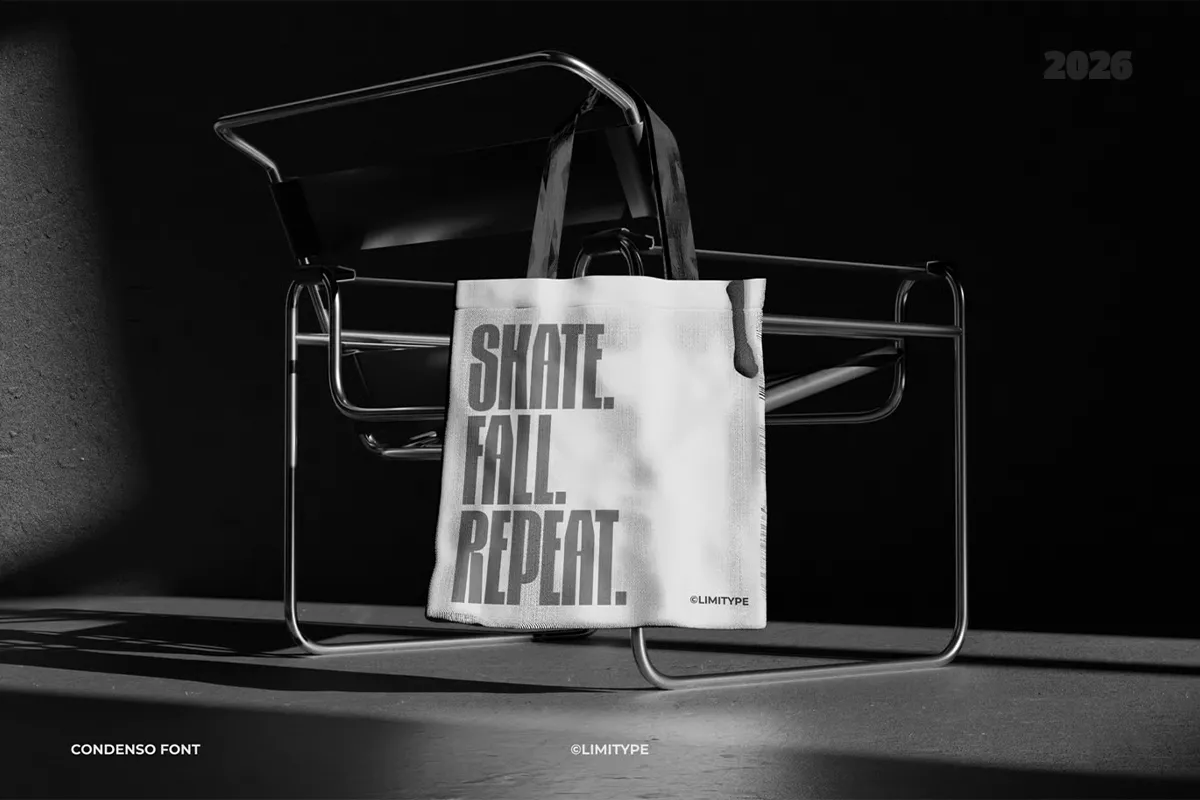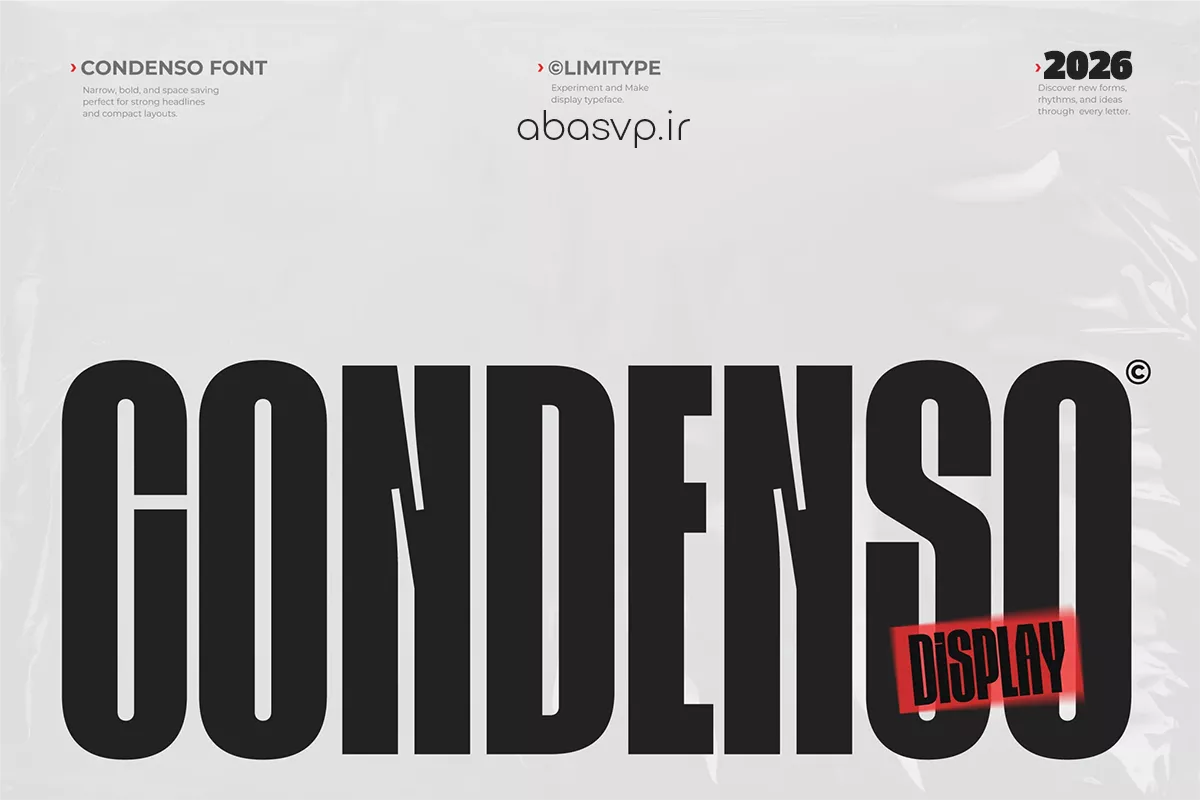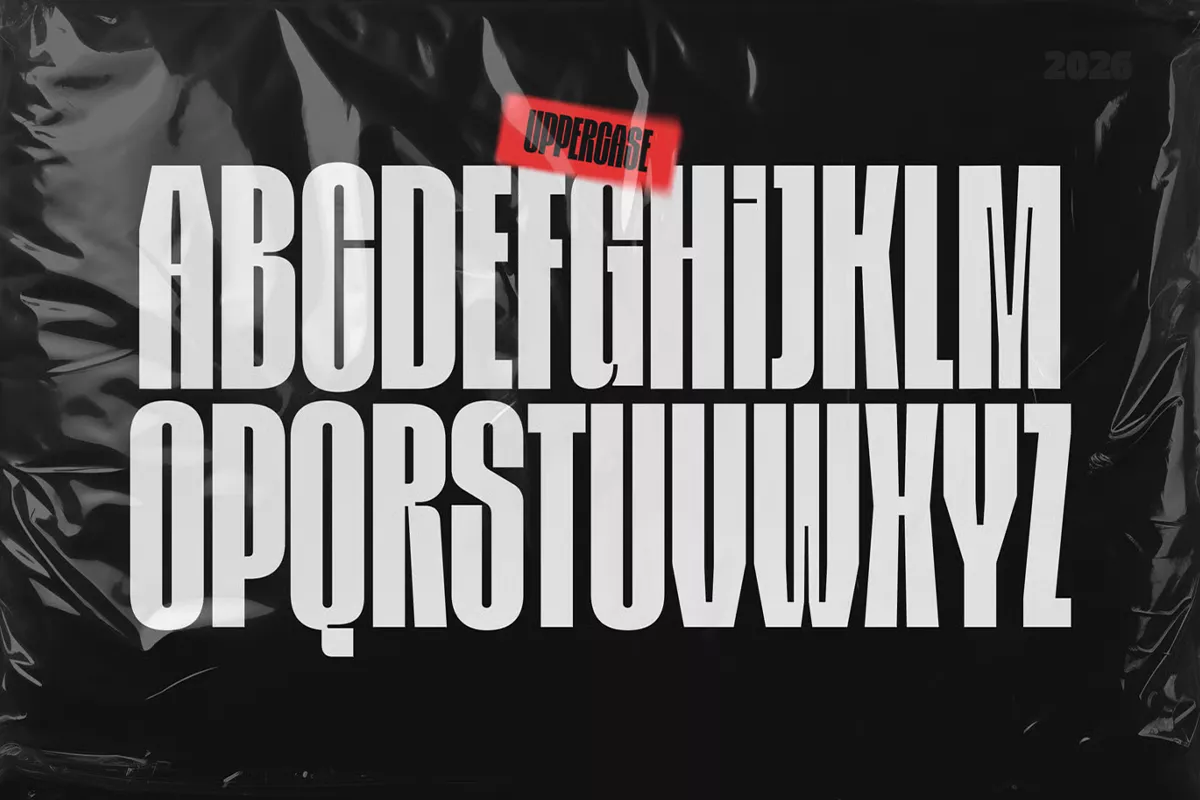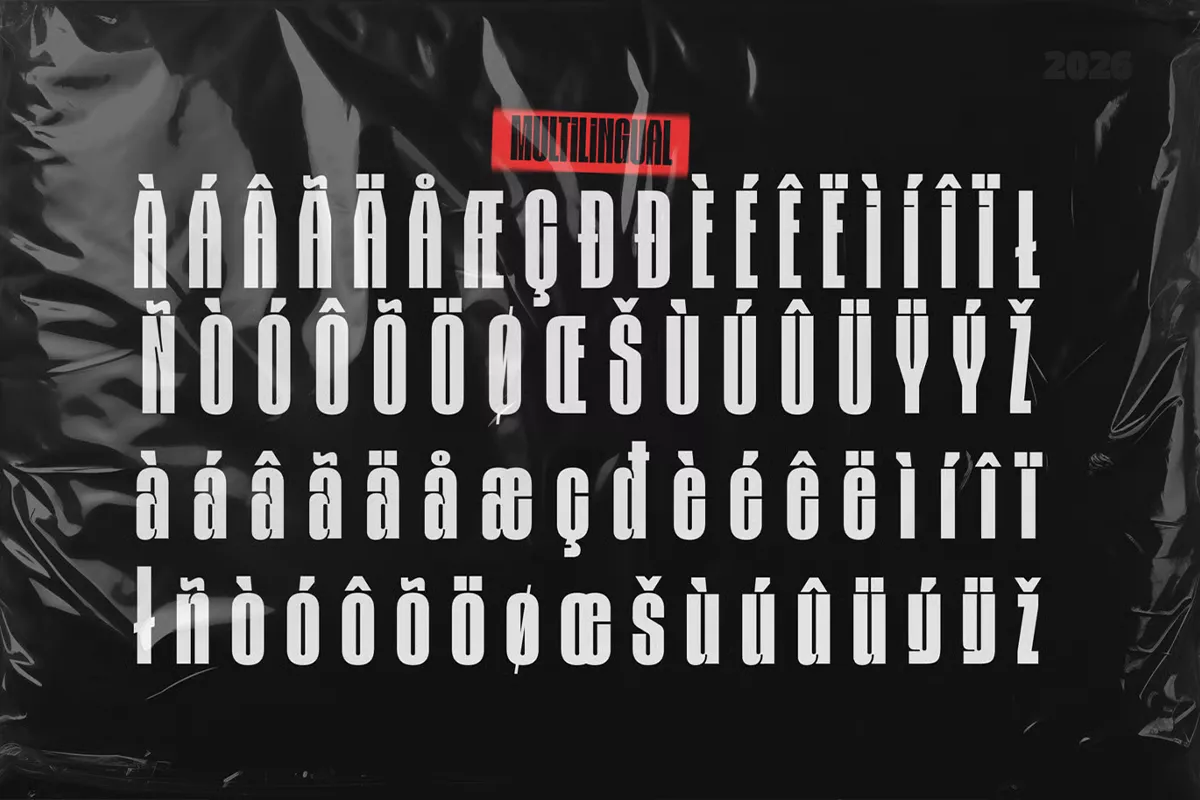
فونت انگلیسی Font Condenso
فونت Font Condenso یک فونت گرافیکی با طراحی مدرن و زیبا برای طراحی است که با یک وزن و با فرمت otf قابل نصب در تمام اپلیکیشن های موبایل و کامپیوتر است که در طراحی کاور های ویدیو و عنوان های تبلیغاتی می توانید استفاده کنید. و این فونت یکی از زیباترین سبک فونت درسال 2026 است که شما بعد از خرید اشتراک دسترسی و میتوانید دانلود کنید.